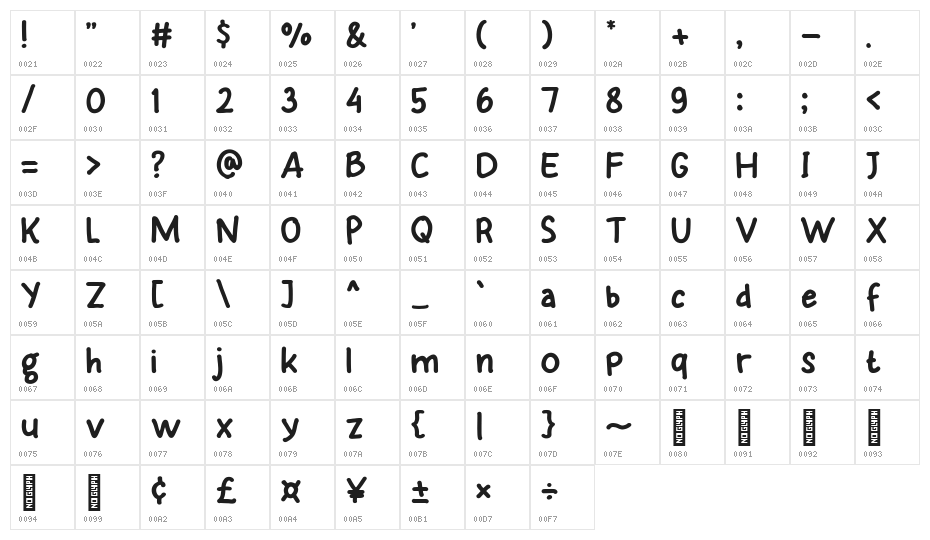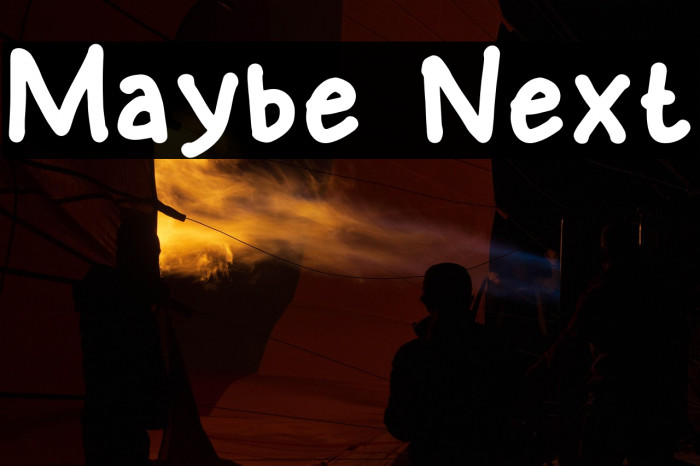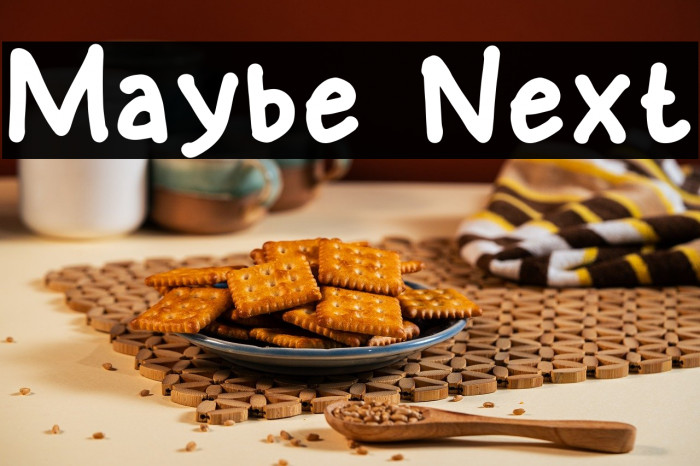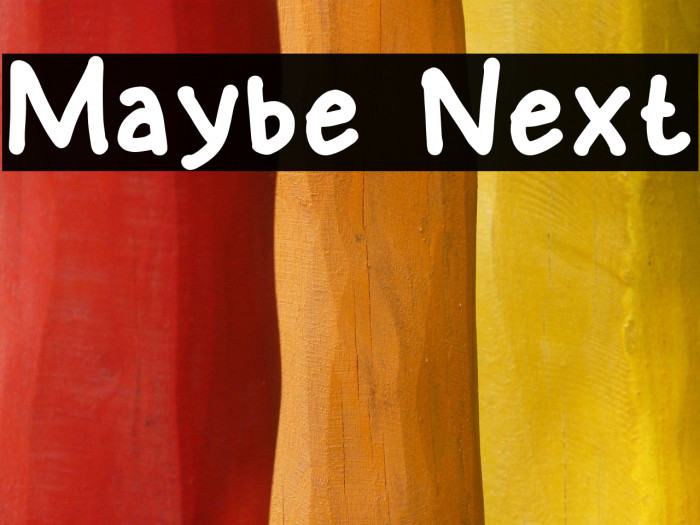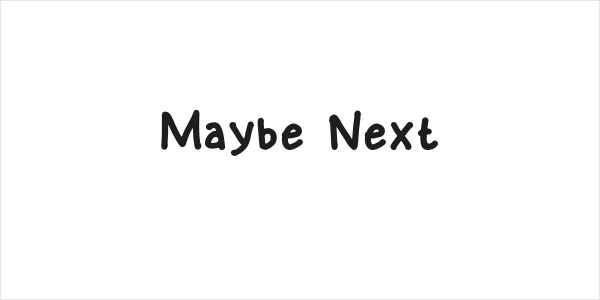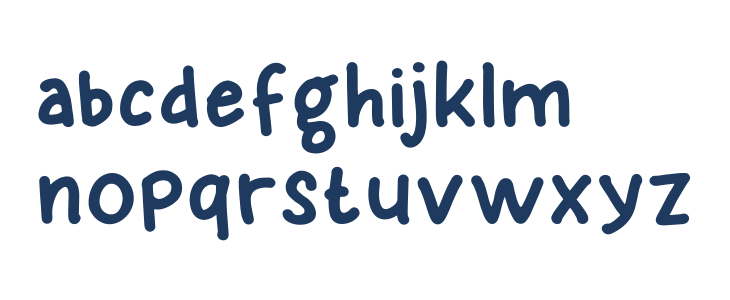
Maybe Next Font
| Style général | Playful |
| Cas d'utilisation | Headlines, Logos, Informal Text |
| Projets proposés | Ideal for children's books, playful branding, greeting cards, and informal invitations. |